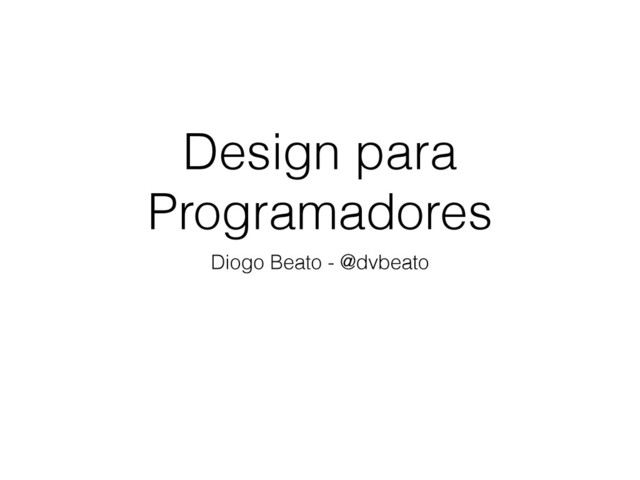
Design para Programadores - Tipografia
papo reto bluesoft, design para programadores - Tipografia
1. Influência do conteúdo • audiência:
idade, genero, cultura. •
tom:
casual, formal, sarcasmo. • propósito:
institucional, informativo, conversão
2. Largura do texto CPL - Characteres por linha Ideal -
50 - 70 Faça responsivo Elimine os widows
3. Lorem ipsum dolor sit amet, consectetur adipiscing elit. Nulla viverra
4. Misturando Estilos • Não misture mesmos estilo • Não misture
mesma classe • Serif títulos e sans-serif body • Humanist-serif - Humanist-sans-serif • Crie contraste • Na dúvida sans-serif.